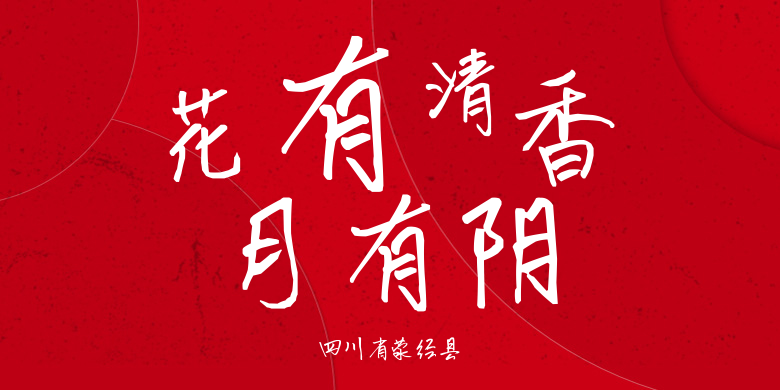
四川省荥经县
四川省荥经县,这款字体结构工整、笔画清晰,兼顾美观与易读性,适用于标题、正文、海报、包装、LOGO 等多种场景。字形优雅稳定,风格百搭耐看,适配日常排版与创意设计,让文字呈现更舒适、更具质感。四川省荥经县一笔一画,皆是细节,以均衡的比例、流畅的线条打造舒适视觉体验,字形端正大气,风格简约现代。无论是商业设计、品牌宣传还是日常排版,都能轻松驾驭,让文字更有格调与力量。四川省荥经县字体下载。